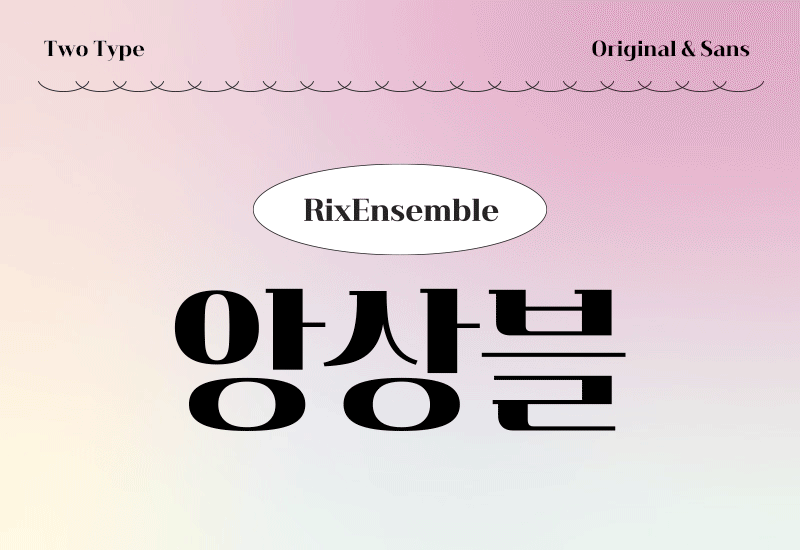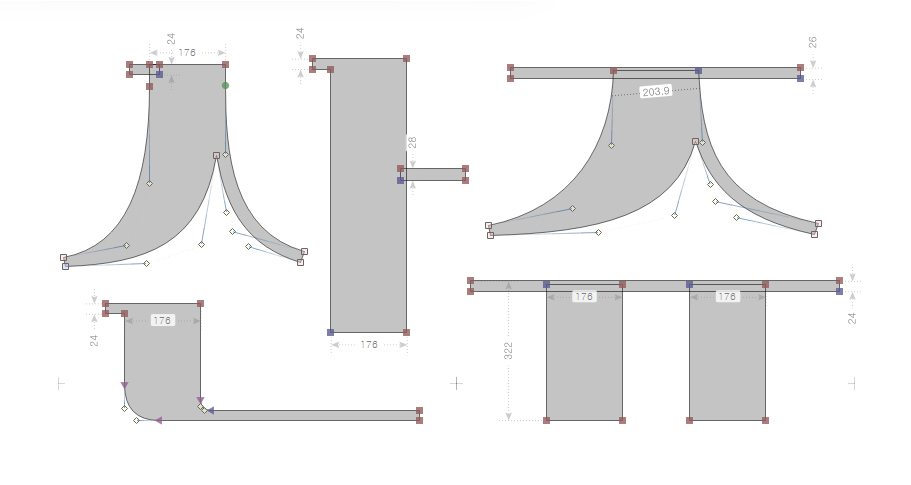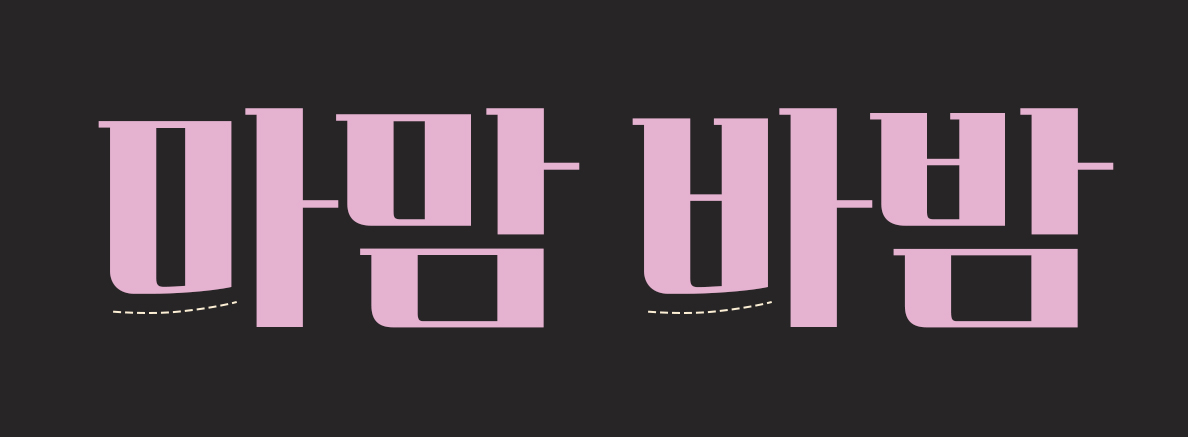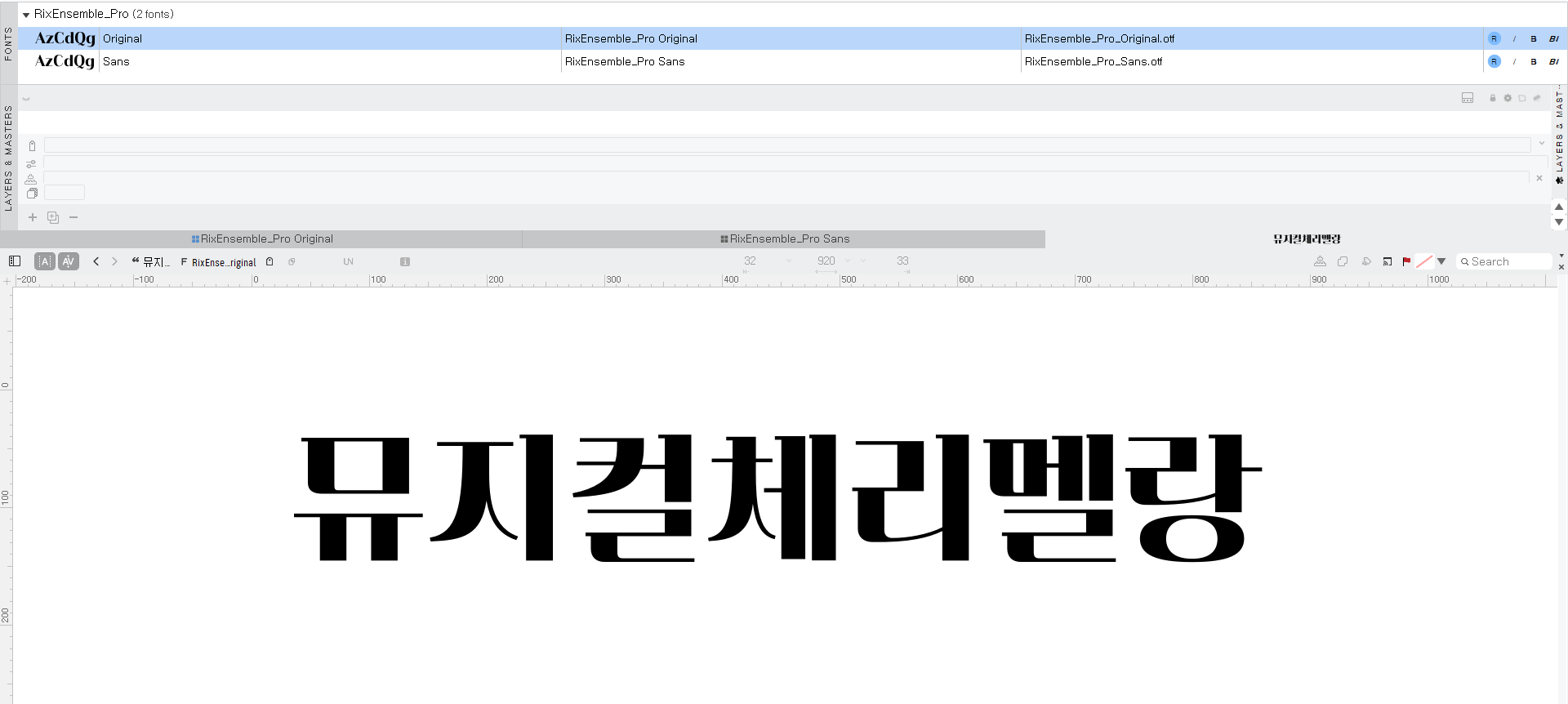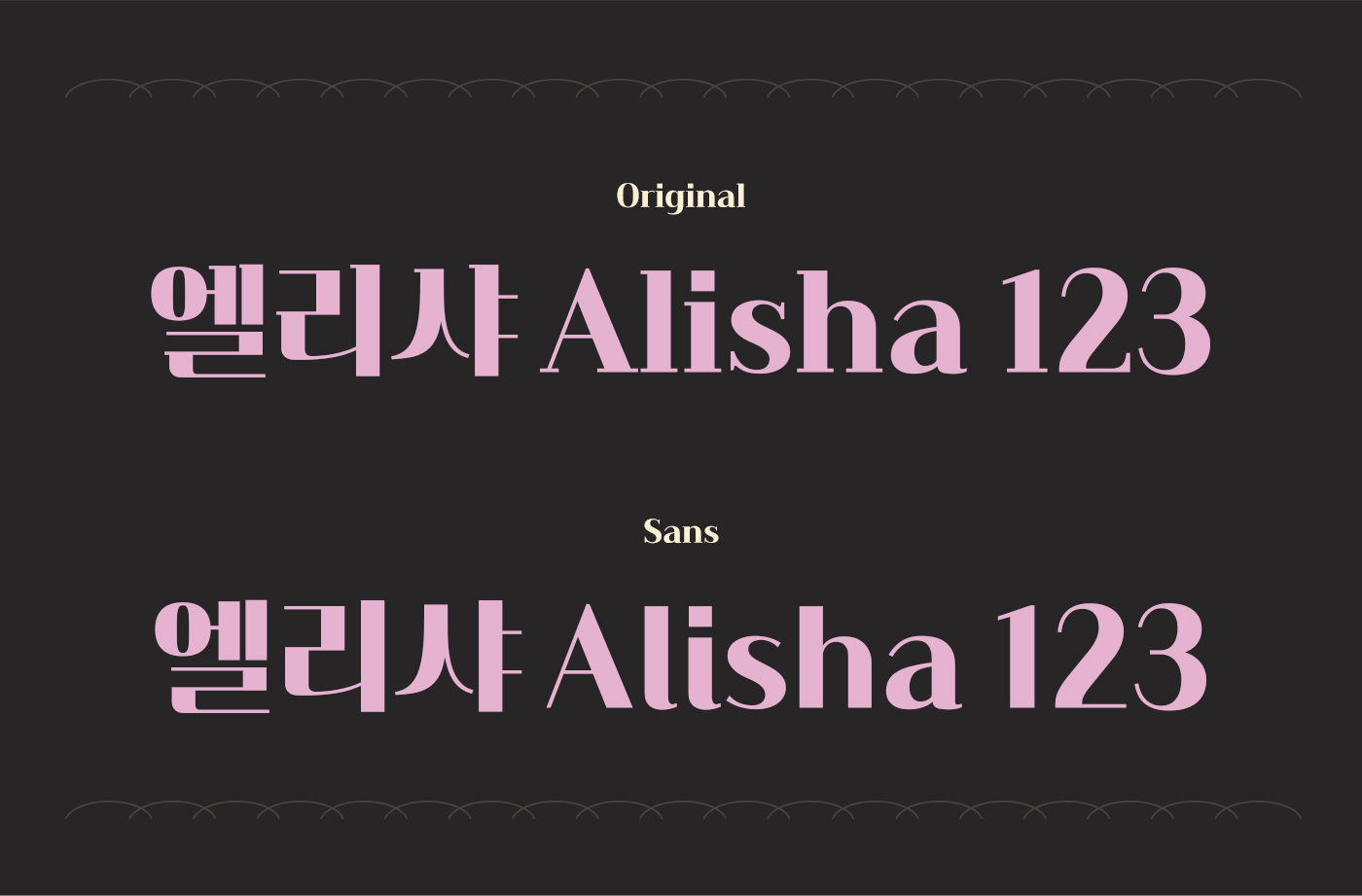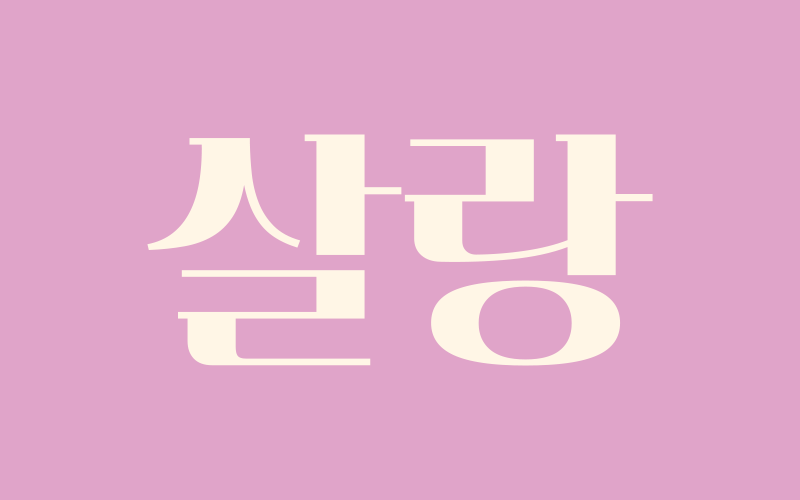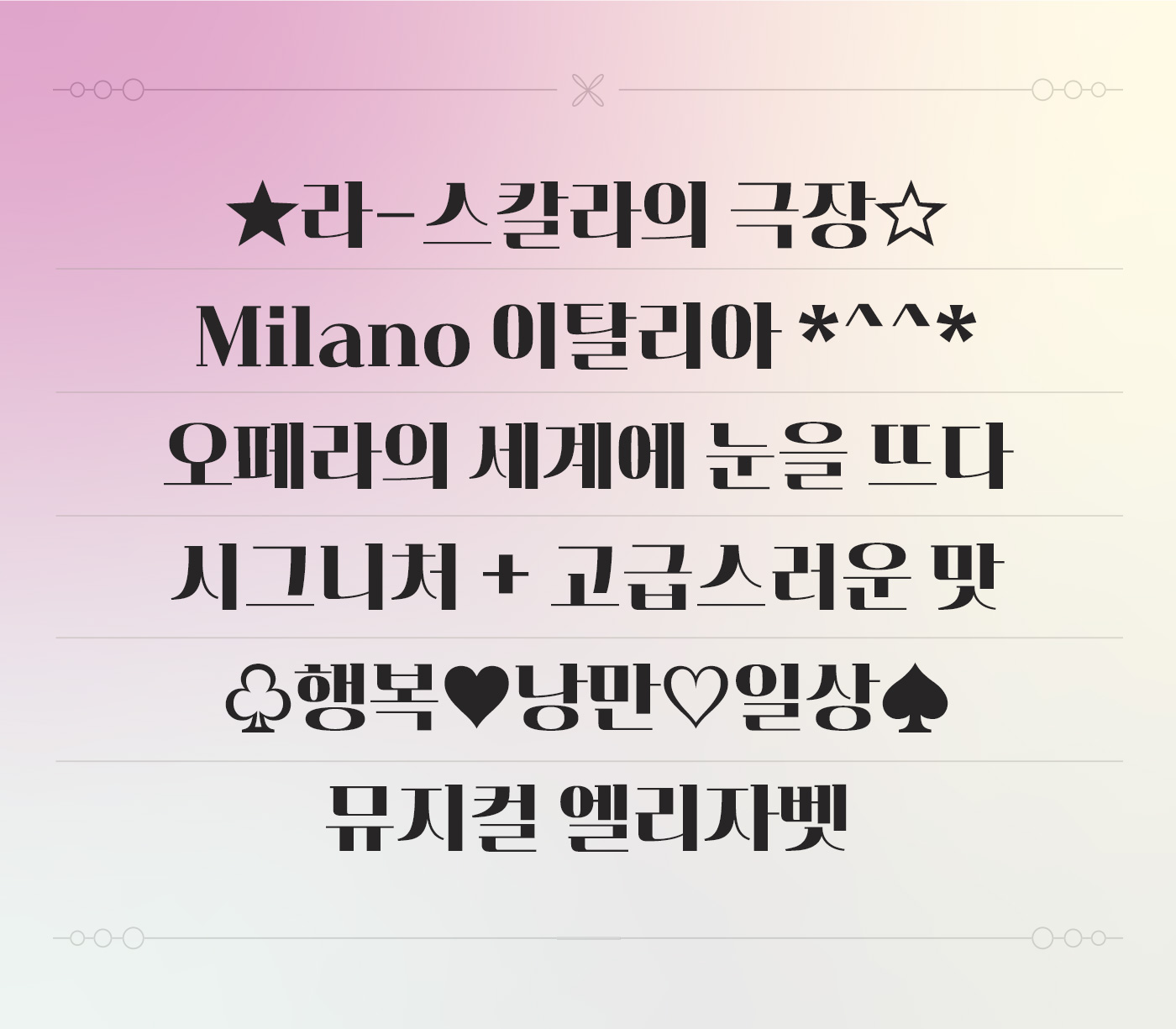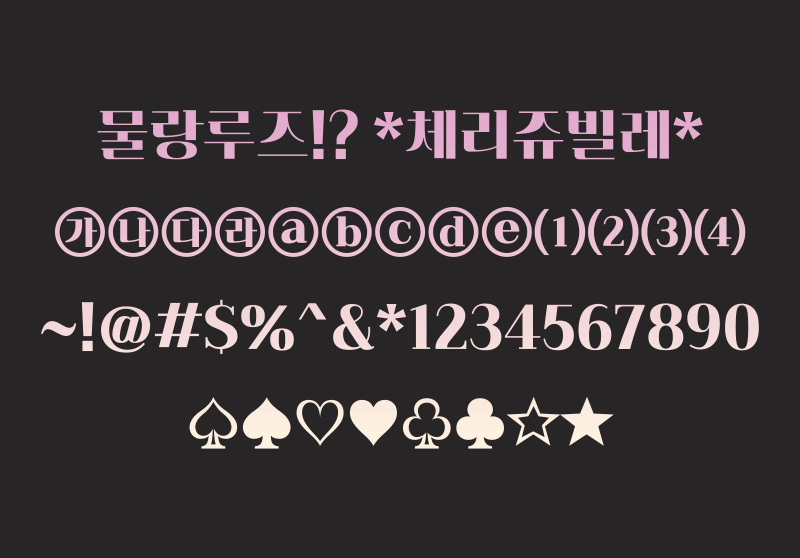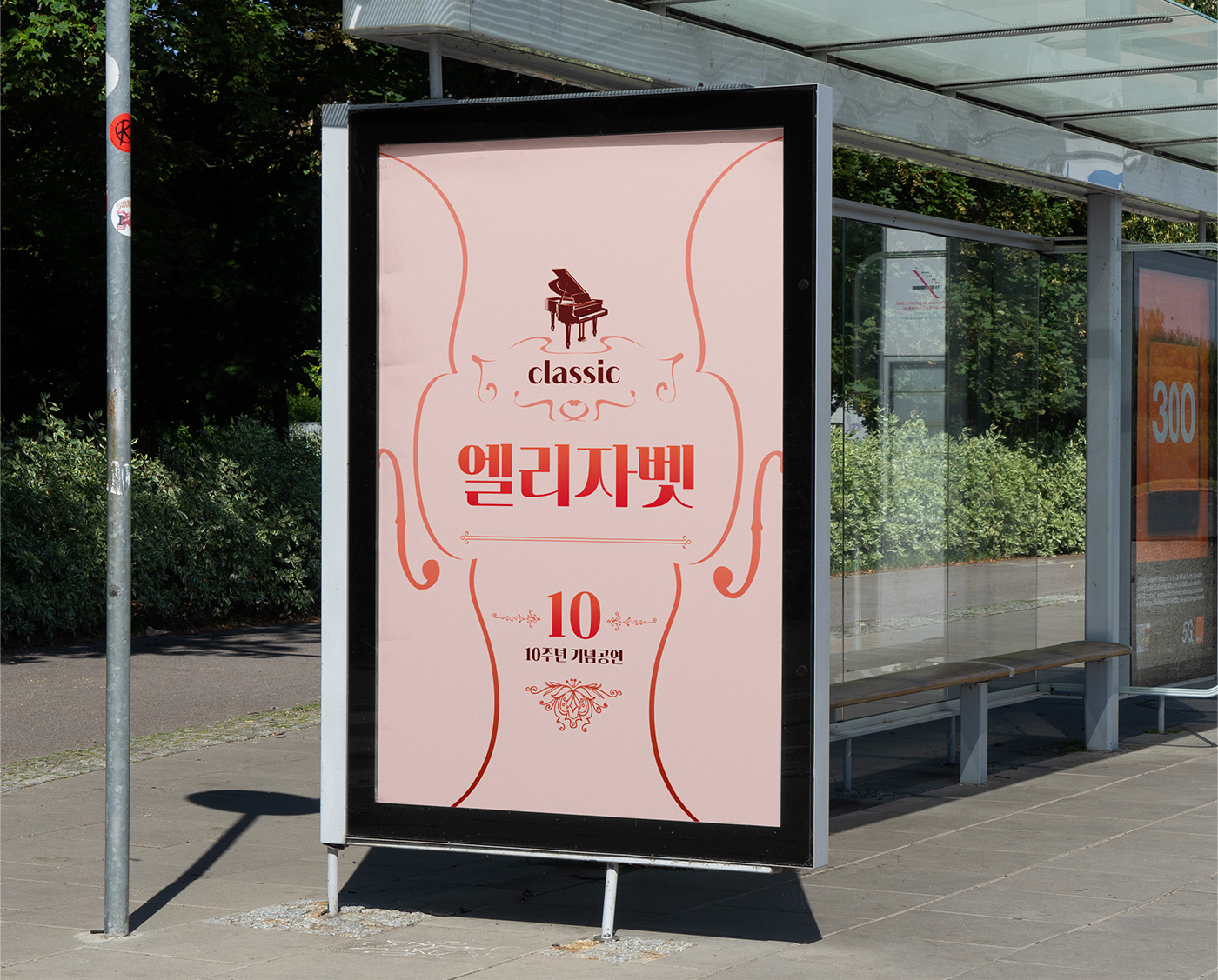
안녕하세요. 행복한 일만 가득할 것 같은 5월의 신규 폰트 「Rix앙상블」을 소개합니다. 첫눈에 세련되고 우아한 인상을 느낄 수 있는 서체로 고급스러우면서 부드럽고 또 최근의 트렌드에 잘 어울리는 모던한 이미지를 갖고 있는 서체입니다. 이번 폰트 제작과 마무리를 맡아 주신 박지영 디자이너를 인터뷰를 통해 만나봤습니다 :)
그렇군요! 5월 신서체 Rix앙상블은 어떤 폰트인가요?
앙상블은 강한 획 대비와 모던한 세리프가 특징인 영문 서체 보도니에 영감을 받아 제작된 폰트입니다.
거기에 유려한 곡선을 더해 우아하고 부드러운 인상을 극대화했습니다. 자음 ㅅ, ㅈ, ㅊ꼴 등에 들어간 곡률과 형태는 경직될 수 있는 분위기를 산뜻하게 풀어줍니다.
이번 서체 패밀리는 특이하게 세리프가 Original이고 산세리프가 두 번째로 들어가 있어요! 그렇게 제작하신 이유가 있을까요?
분류명에 대한 고민이 많았어요. 아무래도 산세리프와 세리프로 내는 쪽이 짝꿍처럼 보이겠죠,,ㅎㅎ 그렇지만 첫 기획이 세리프가 있는 버전이기도 하고, 형태적으로 더 마음에 들어 메인으로 보였으면 했습니다. 이 부분은 기획하신 지윤님을 포함한 다른 동료들과 함께 결정한 부분이기도 합니다.
Rix앙상블 어떻게 활용하면 좋을지.
헤드라인으로 제작된 서체이기 때문에 고급스러운 이미지의 광고 매체나 포스터, 영상 타이틀로 적절하다고 생각합니다. 상황에 따라 영상의 포인트 자막용으로 써도 괜찮을 것 같아요.
우아함과 모던함의 앙상블
강한 획대비와 유려한 곡선으로 우아한 인상을 가진 Rix앙상블은 모던한 세리프 디자인의 Original과 깔끔하고 부드러운 Sans 2종으로 제작되었습니다.
기본적인 골격은 단단하고 획의 대비가 강하지만, 봄의 따스하고 기분 좋은 바람처럼 자연스럽고 유려한 곡선이 자소 디자인에 가미되어 부드러운 이미지를 줍니다.
긴 글을 써보면 글자 자체의 개성과 우아함을 느낄 수 있는데요, 고급스러운 패션 브랜드나 클래식 음악, 뮤지컬 등 예술적인 이미지가 연상되는 독보적 매력의 서체입니다. 영문, 숫자, 기호 등에 동일한 특징이 적용되어 혼용 시 조화롭습니다.
디자인 자체만으로도 컨셉추얼한 이미지에 접목하기 좋기 때문에 여러 매체에 사용할 수 있습니다. 포스터나 배너에 활용할 경우 확실한 주목성을 가질 수 있는 서체입니다.
Sans로 활용할 경우 화려함이 덜어지고 깔끔하고 모던한 맛이 더해져 브랜드의 이미지가 되는 로고 디자인으로도 적합합니다. 작은 디테일의 차이가 멋진 브랜딩을 가능하게 합니다.